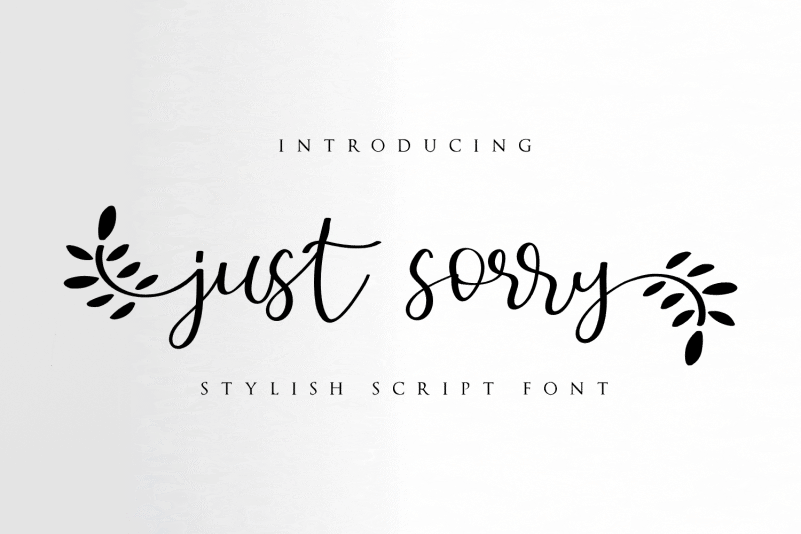
Ajustando-se ao formato solicitado, aqui está uma descrição em português para a página de download do tipo de fonte ‘Just Sorry Calligraphy Font’: “A Justamente Desculpe é uma tipografia script de caligrafia. Ela incorpora linhas fluidas e variadas, além de caracteres exuberantes com alternativas impressionantes. Esta fonte traz uma sensação autêntica do estilo da caligrafia, perfeita para criar cartões de agradecimento encantadores, artes de estacionamento bonitas e postagens de mídia social chamativas. Além disso, oferece três tipos alternativos para minúsculas, além das características que incluem alternativas ao folha. Perfeito para designers de gráficos que buscam uma fonte única e vibrante para seus trabalhos.” Esta descrição mantém um tom informativo e convidativo, sem inventar novas características ou informações, respeitando o nome da fonte em cada frase como solicitado.
Designer: Nuryanto Dwi